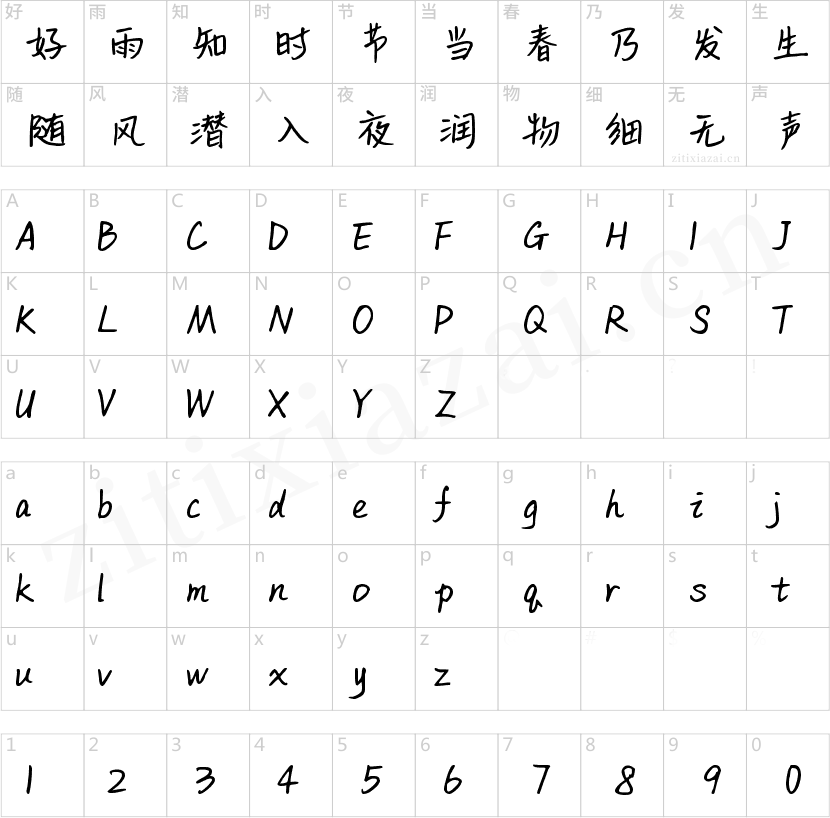
Aa野蛙蛙
Aa野蛙蛙,这款字体结构工整、笔画清晰,兼顾美观与易读性,适用于标题、正文、海报、包装、LOGO 等多种场景。字形优雅稳定,风格百搭耐看,适配日常排版与创意设计,让文字呈现更舒适、更具质感。Aa野蛙蛙一笔一画,皆是细节,以均衡的比例、流畅的线条打造舒适视觉体验,字形端正大气,风格简约现代。无论是商业设计、品牌宣传还是日常排版,都能轻松驾驭,让文字更有格调与力量。Aa野蛙蛙字体下载。
Aa野蛙蛙字体
Aa野蛙蛙是一款非常具有艺术性的字体,它的设计灵感来源于对古典艺术的研究,同时又融入了现代字体设计的元素。字形优美,笔画粗细变化自然,给人以大气、典雅的感觉。Aa野蛙蛙是一款既传统又现代的字体,它的设计充满艺术感,美观大方,实用性也非常强。无论是对于设计师还是对于普通读者来说,都是一种非常不错的字体选择。Aa野蛙蛙适合用于具有艺术感的场合,比如海报、宣传单张、书籍封面等。由于其字形流畅且具有动态感,也适合用于大量的文本排版,如报纸、杂志等。